コッコアポ
クラシエの漢方製剤「コッコアポ」シリーズ。「コッコアポ」シリーズは、クラシエのセールスポイントである漢方処方のノウハウを活かし、それぞれの体質や症状によりタイプ別で選択できる漢方製剤になっている。
コッコアポEX錠
腹まわりに余分な脂肪が多く便秘がちな人間にオススメの漢方製剤。脂質代謝を上げて余分な脂肪を分解・燃焼して減らせる。
コッコアポG錠
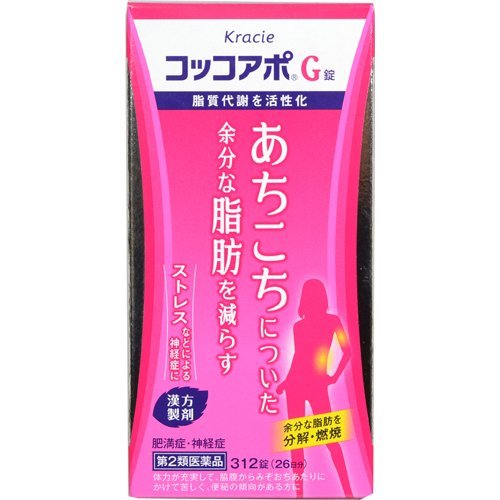
ストレスなどでわき腹からみぞおちあたりにかけて苦しい人間にオススメの漢方製剤。脂質代謝を上げて、余分な脂肪を分解・燃焼して減らせる。
コッコアポL錠
疲れやすく、加齢などで筋肉の力が弱くなった人間にオススメの漢方製剤です。脂質代謝を上げて、余分な脂肪を分解・燃焼して減らせる。
クラシエ当帰芍薬散錠
冷え症でむくみやすい体型の人間にオススメの漢方製剤。身体を温めながら水分代謝を高め、余分な水分を取り除くことで、むくみ、足腰の冷え症を治せる。
「コッコアポ」シリーズパッケージのキャッチコピーにダイナフォント「娥眉明朝体」が採用
「コッコアポ」シリーズのパッケージに記載されたキャッチコピーのテキストにはダイナフォント「娥眉明朝体」が採用されている。
採用理由は、ビューティーのイメージが強く出ているため、コッコアポの商品イメージにマッチしていたための採用とのこと。
娥眉明朝体
明朝体をベースに細長く弧を描いた眉の形をイメージしたストロークから洗練された女性の柔らかさや優しさを表現した明朝体。